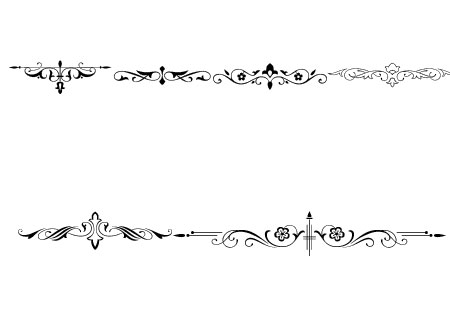
почему это шрифт, а не кисть?
не получается им "писать"
как пользоваться? (в шрифтах вижу, но как выбрать определенного вида завитушку? ведь в одном шрифте их несколько)
очень красивые, пригодятся )
Нет предела человеческой фантазии. Спасибо, удивили!
Мне как раз для меню ^^
Великолепный Шрифт
А ещё так можна татуровку на теле лепить...
Красотень х) Можно использовать даже не как шрифт, а как просто украшение.
ниче в нем и не понятно))